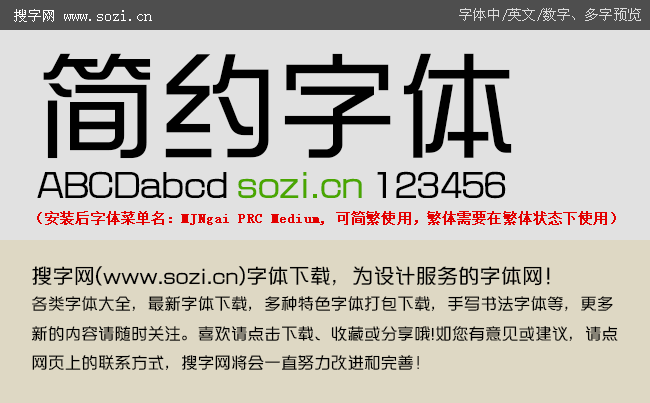
簡(jiǎn)約字體
搜字網(wǎng)給大家提供一款簡(jiǎn)約字體手機(jī)中文字體下載。這款手機(jī)字體是一款現(xiàn)代設(shè)計(jì)藝術(shù)字體綜藝體,綜藝體是黑體的一種變體,也是藝術(shù)字的一種。特點(diǎn)是筆劃更粗,盡量將空間充滿。同時(shí)為了美觀,對(duì)拐彎處的處理較為圓潤(rùn)。適合喜歡手機(jī)字體個(gè)性一些的朋友在手機(jī)上安裝使用。